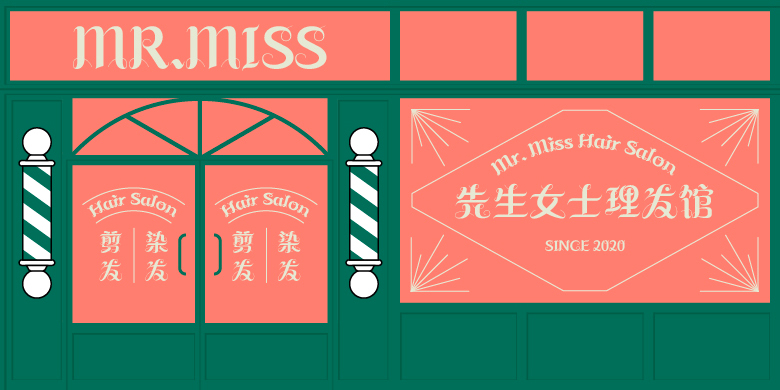
方正纖舞體 詳情頁
方正纖舞體字體下載6字重 FZXianWuTiS
纖舞體是以拉丁文“Script”形態(tài)演繹的中文花寫字體。“Script”字體源遠流長,在西方非常普遍和流行,但在筆畫繁復的中文字體中演繹時,難度甚高。作者以驚人的毅力,用了兩年多時間終于攻克完成 “纖舞體”創(chuàng)作。纖舞體風姿綽約,曼妙動人,適合高檔時裝、化妝品、手袋、鞋類等包裝宣傳以及纖體美容類產(chǎn)品宣傳,也適合生日卡、情人卡、圣誕卡和各種賀卡設(shè)計等等。